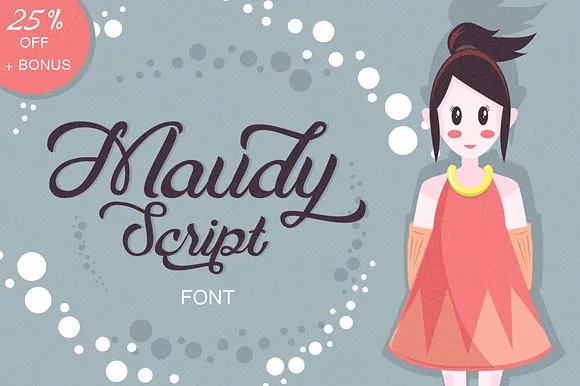
Introduzimos a Maudy Font! Este tipo de letra fornece uma opção moderna e versátil para seus projetos criativos. Com sua escrita desenhada com um pincel, essa fonte é perfeitamente adaptável a variados usos, incluindo logotipos, embalagens, títulos de capas de livros, cartazes, camisetas, convites de casamento e cartões de felicitações. Ideal para designers que buscam uma opção estilosa e atual, a Maudy oferece um blend entre escrita natural e tipografia moderna. Suas linhas robustas e seus tons sóbrios permitem que seja usada em diversos contextos sem perder sua elegância. Seja para criar um design minimalista ou ornamental, a Maudy Font é uma escolha segura e versátil.